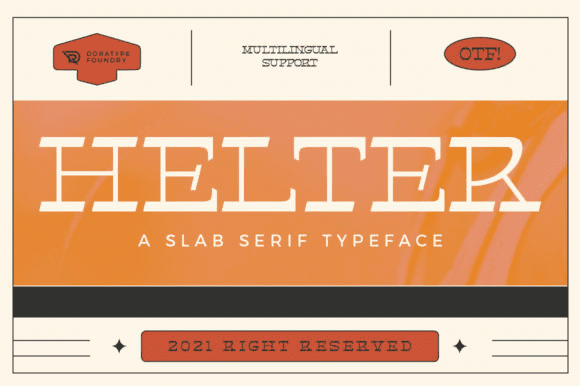
Название: Helter Font
Helter - это смелый и шикарный шрифт с наклонной засечкой.
Независимо от темы, этот шрифт станет прекрасным дополнением к вашей библиотеке шрифтов, поскольку он способен улучшить любое творение.